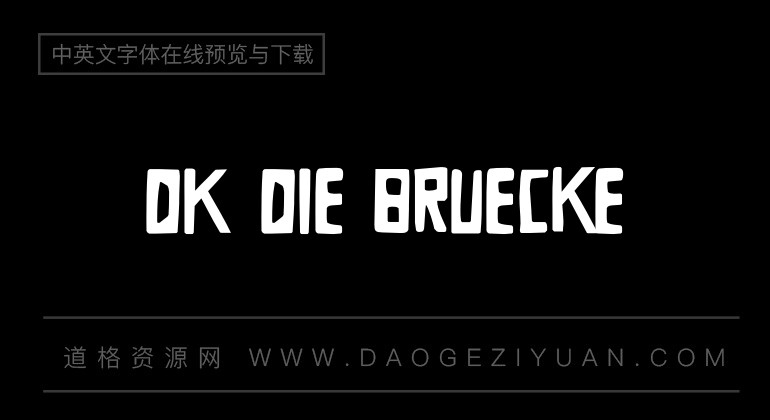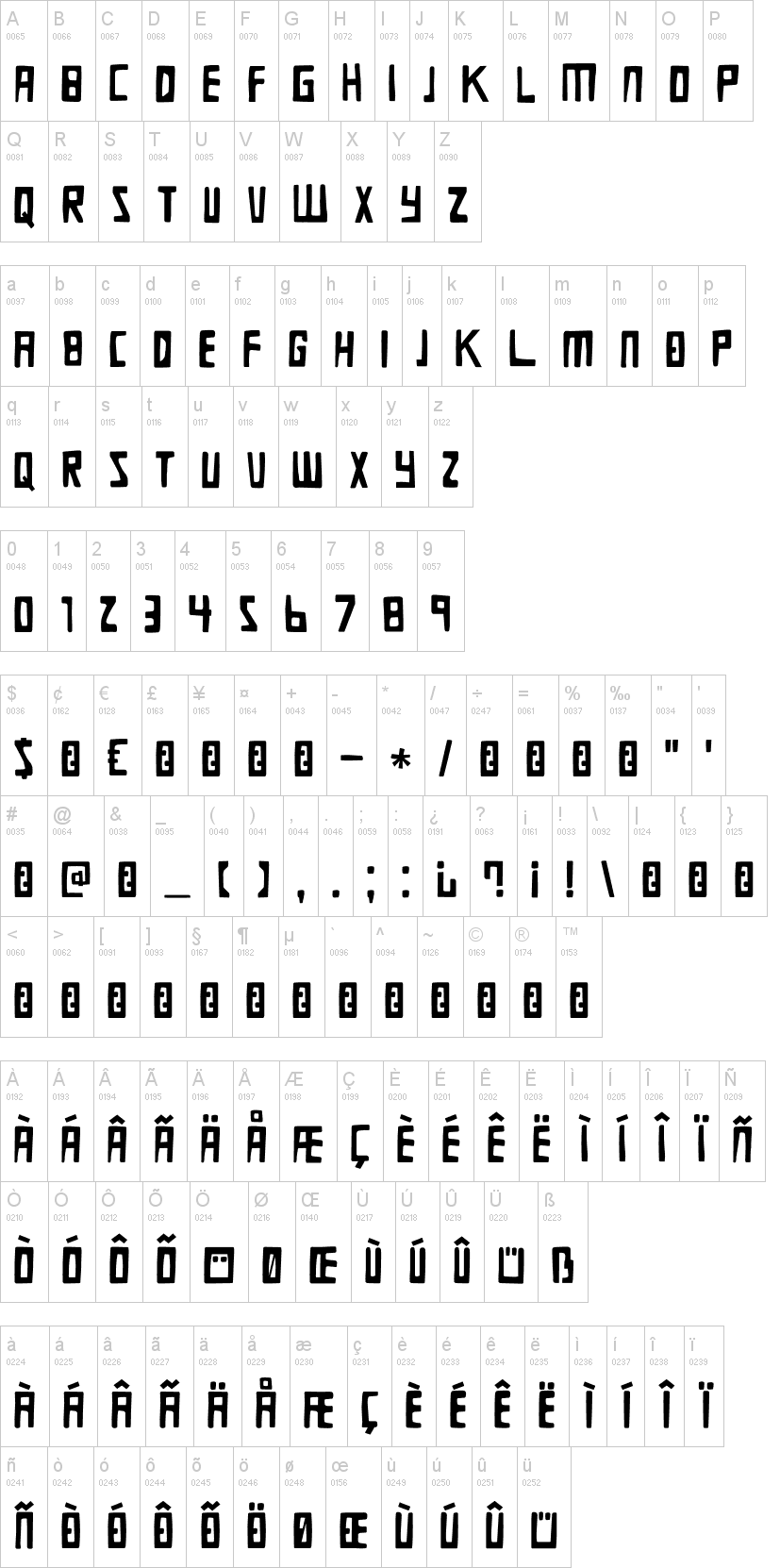
DK Die Bruecke 是一款粗体字体,由德国设计师Dieter Krieger设计,它的特点是有一种极具特色的视觉效果。DK Die Bruecke字体采用简洁的线条设计,在设计中突出了字母的特点,使字体看起来更加精炼和大气。此外,它还具有良好的可读性,适用于大型标题和小型段落文字,可以让您的文字更加突出。内容介绍
DK Die Bruecke是一款非常不错的手写艺术字体,具有很好的视觉感,适合于文化类的宣传设计、商业类品牌的广告和产品包装设计以及个性化文字排版等较多场景。